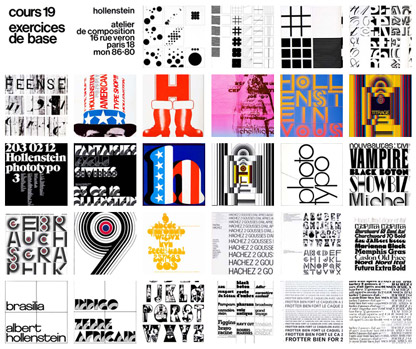
C’est bien avant la création de l’Helvetica par Max Miedinger en 1957 qu’Albert Hollenstein, typographe suisse quitta les montagnes romandes pour rejoindre Paris avec juste un sac à dos et son Rolleiflex (1953). Enfant de Norman McLaren et de Guy Peelaert il allait révolutionner le paysage graphique français. J’ai publié un article dans étapes #131 qui retrace sa bio la plus complète, aussi je voudrais juste apporter quelques compléments d’infos sur ce boyscout du graphisme. Vous trouverez d’ailleurs la galerie des travaux de sa société ici.
Albert Hollenstein n’a jamais dessiné et produit personnellement un caractère du début jusqu’à la fin. Ce n’était pas un moine comme Albert Boton qui travailla pour lui juste avant de filer chez Delpire puis Carré Noir plus tard. Le caractère Brasilia, il en a jeté sans doute les bases sur une feuille de papier mais tout comme Stanley Morison il confiait ses idées à d’autres, plus patients pour les réaliser. Lorsqu’il crée l’atelier Hollenstein au milieu des années 50, il s’installe d’abord rue Germain Pilon puis au 16 de la rue Véron sur les collines de Montmartre. C’est là qu’à peine le caractère de Miedinger commercialisé par la fonderie Haas et son nouveau dirigeant, Alfred Hofmann qu’Albert va pour la première fois en France proposer aux agences de publicité et directeurs artistiques de leur composer leurs textes en Helvetica et en plomb manuel, je vous prie ;-). La carrière d’Hollenstein fut hélas écourtée par un accident malheureux sur les côtes italiennes mais témoigne d’un esprit universel, qui embrassait musique, images et typo avec le sens du brassage des cultures.
Il créa les cours 19 qui connurent un succès retentissant dans le micro-cosmos parisien. La première fois que l’on osa aborder en France le graphisme sous l’angle architectural et structurel. Imaginez Walter Diethelm ou Armin Hofmann ou Josef Müller-Brockmann qui eurent donné des cours dans la capitale des arts nouveaux et de la frilosité à l’égard de tout ce qui venait du Bauhaus germanique. Mais les Français aimaient bien la Suisse, et Albert eu ce don de savoir faire partager ses passions d’autant qu’au moment même où il laissait Jacques Roch et Hans Rudolf Lutz continuer sans lui l’aventure du cours 19, il était déjà ailleurs, inventant la phototypo et les diaporamas géants qui vous projetaient des murs images avec 48 carrousels à la fois.
Le talent d’Albert Hollenstein: un découvreur de talent qui sut s’entourer des meilleurs graphistes du moment, André Chante (alias Andy Song), Daniel Sinay, Albert Boton, Jean Alessandrini n’en sont que quelques uns des brillants représentants. Et ce découvreur de talent était doublé d’un don pour le travail. Il bossait sans relâche jusqu’à l’extrême. Il allait lui même au contact des clients et sut créer un esprit Hol qui envahit le tout Paris des Agences de Publicité. De grandes marques lui confiaient leurs budgets de comm. tel Simca ou IBM pour lesquelles chaque fois il inventait un processus de création adapté aux messages à délivrer. Loin d’être un suiveur, il créait la mode, tant pour les caractères, les logos, que pour les visuels de magazines ou de l’édition. Pour faire court, je vous invite à déguster avec délectation les quelques images clés de la galerie que j’ai réalisé en son hommage.
affiche pour une grande conférence qu’Albert organisa pour promouvoir la typographie américaine. Il y invita Lou Dorfsman, et Ronne Bonder et Aaron Burns.
enveloppe d’expédition des «compos» Hollenstein destiné à promouvoir les typos et l’esprit Hol. Ici l’enveloppe de Noël.
Affiche promotionnel pour les créations «fantaisies» de l’atelier Phototypo.
affiche de vœux fin d’année. (1971)
couverture de catalogue pour les caractères de phototitrage